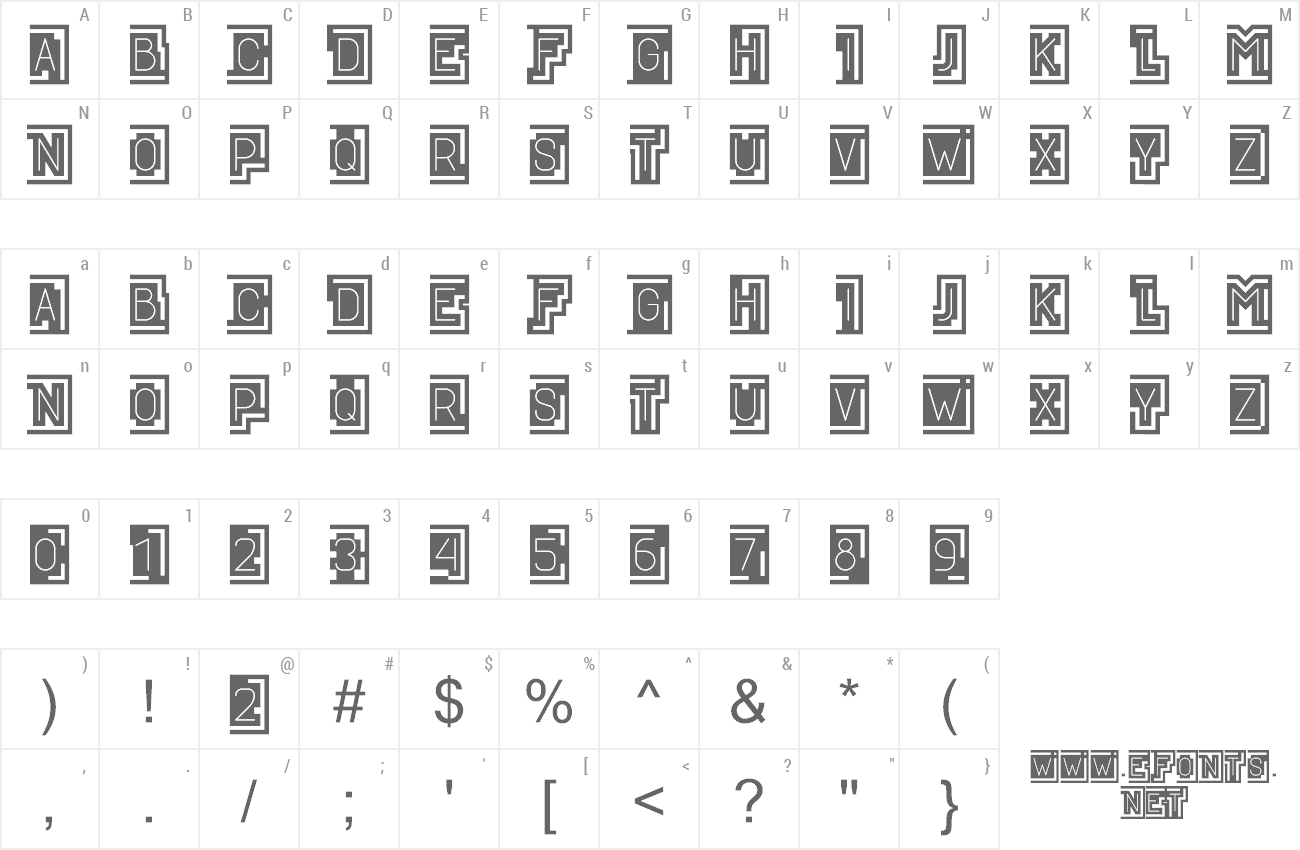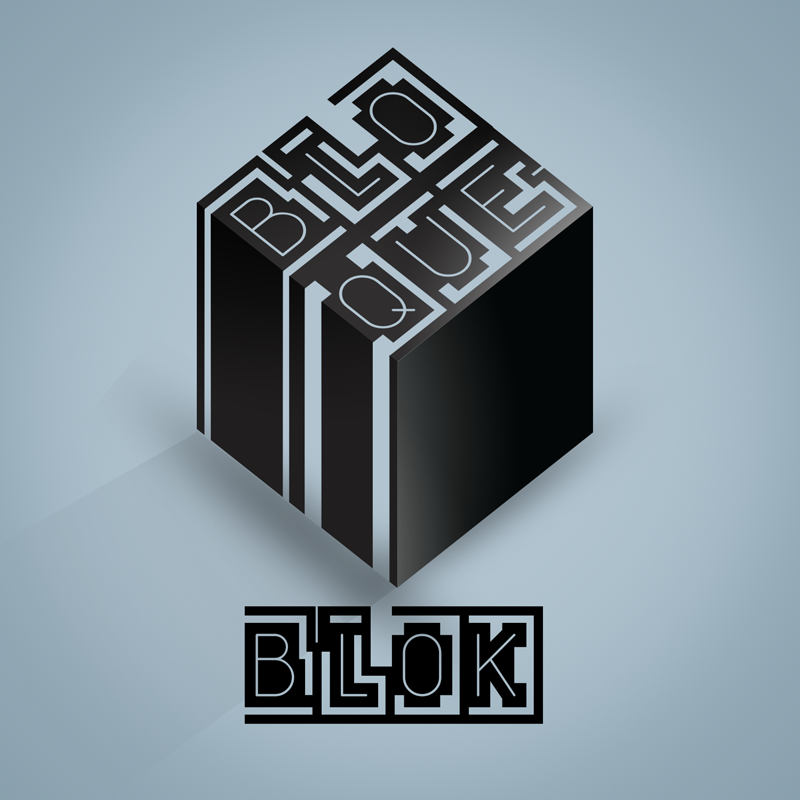
Preview and download Blok Font. Created by Marco Antonio Ramirez Murga in Techno Square styles with 100% Free license.
| Font name: | Blok |
| Categories | Techno, Square |
| Author: | Marco Antonio Ramirez Murga |
| Note by Marco Antonio Ramirez Murga | |
| Fuente BLOK, pensada para textos cortos, en esta primera versi�n ponemos a disposici�n de manera abierta y gratuita, esperamos que sea �til. |